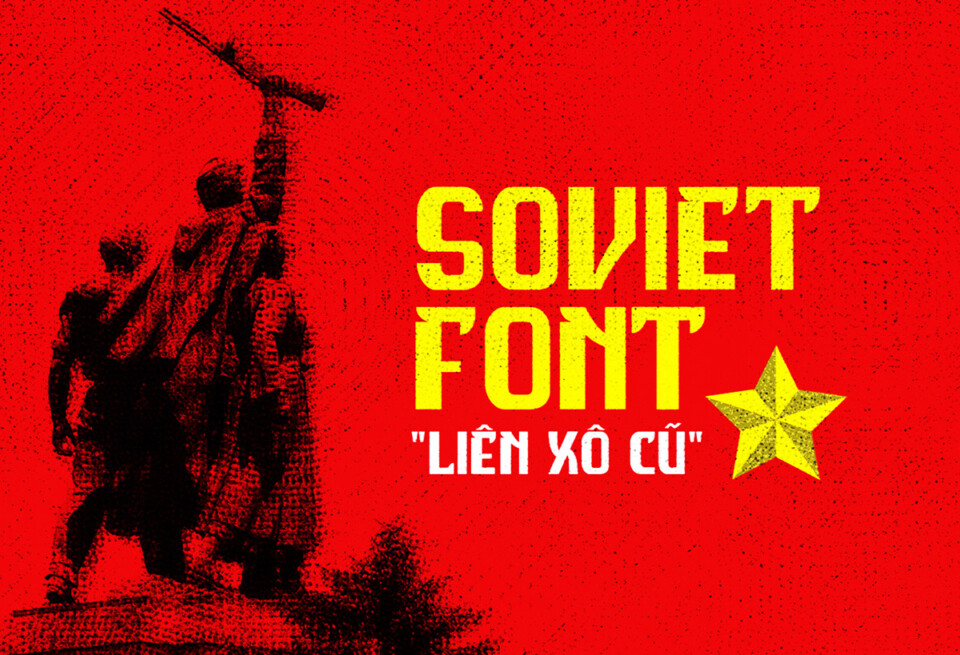
Font Tiếng Việt Soviet
Tổng hợp các mẫu Font Tiếng Việt Soviet ấn tượng cho thiết kế cổ điển
Sức hút của dòng Font Tiếng Việt Soviet trong thiết kế đồ họa
Trong thế giới sáng tạo hiện nay, việc sử dụng các mẫu Font Miễn Phí mang phong cách hoài cổ đang trở thành xu hướng mạnh mẽ. Font Tiếng Việt Soviet là bộ sưu tập các kiểu chữ lấy cảm hứng từ nghệ thuật đồ họa và kiến trúc của kỷ nguyên thế kỷ 20. Những bộ chữ này không chỉ đơn thuần là công cụ soạn thảo mà còn là phương tiện truyền tải cảm xúc mạnh mẽ về một thời kỳ lịch sử đặc biệt. Với các đường nét vuông vức, khỏe khoắn và mang tính biểu tượng cao, bộ phông chữ này giúp các bạn học sinh và nhà trường dễ dàng tạo ra những ấn phẩm truyền thông độc đáo, đậm chất cổ điển nhưng vẫn rất hiện đại.
Đặc điểm nổi bật của phong cách chữ Soviet Việt hóa
Điểm nhận diện rõ nhất của Font Tiếng Việt Soviet chính là cấu trúc hình khối dày dặn và độ tương phản thấp. Các ký tự thường được thiết kế theo dạng không chân (sans-serif) hoặc có chân lớn, tạo cảm giác bền vững và uy nghiêm. Khi được Việt hóa, các dấu thanh đã được tinh chỉnh khéo léo để đảm bảo tính thẩm mỹ mà không làm mất đi tinh thần gốc của bản thiết kế. Đây là lựa chọn hoàn hảo cho các dự án làm poster, bìa sách lịch sử hoặc các video clip mang phong cách vintage.
Ứng dụng Font Tiếng Việt Soviet vào thực tế
Bạn có thể sử dụng bộ chữ này để thiết kế bảng tin trường học, làm bài thuyết trình PowerPoint hoặc tạo logo cho các câu lạc bộ. Việc kết hợp màu sắc như đỏ, vàng hoặc các tông màu trầm sẽ làm nổi bật tối đa vẻ đẹp của dòng chữ này. Để bắt đầu sáng tạo, bạn hãy truy cập ngay vào kho Font Miễn Phí, Font Việt Hóa, Font Tiếng Việt Soviet để tìm kiếm phiên bản phù hợp nhất. Việc sử dụng đúng phông chữ sẽ giúp thông điệp của bạn trở nên chuyên nghiệp và giàu sức biểu cảm hơn bao giờ hết.